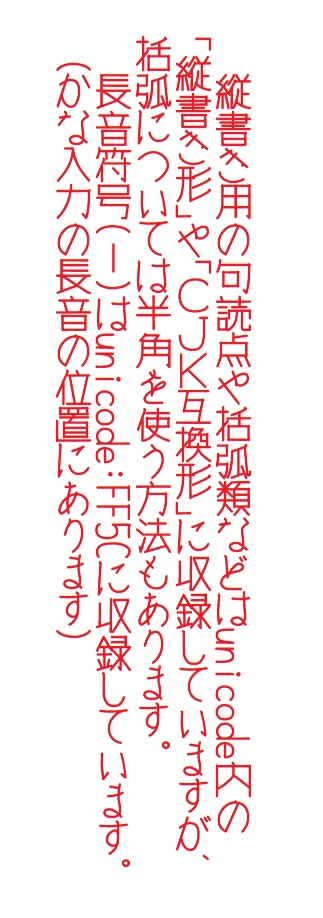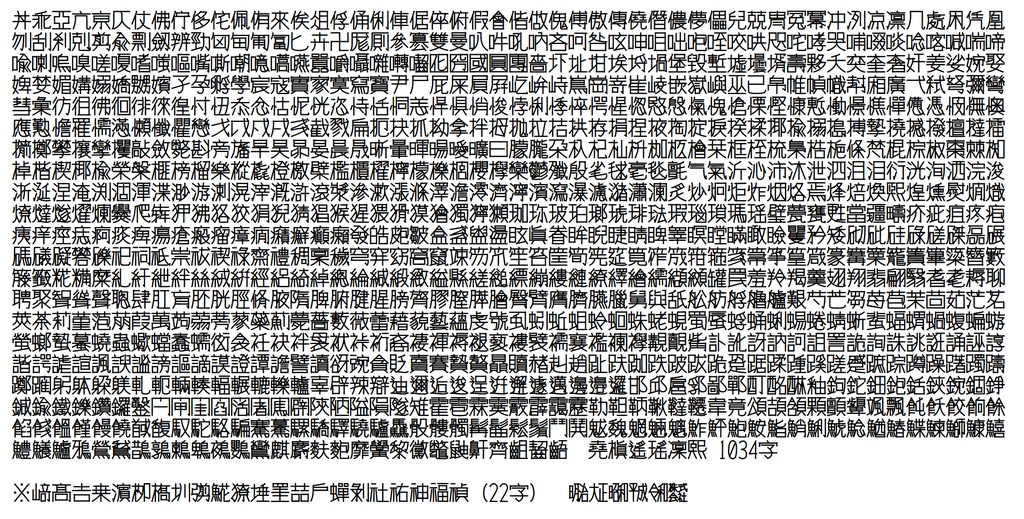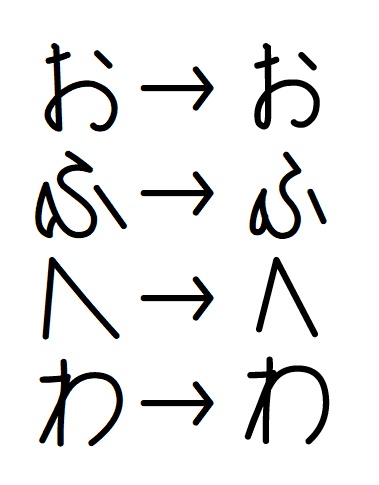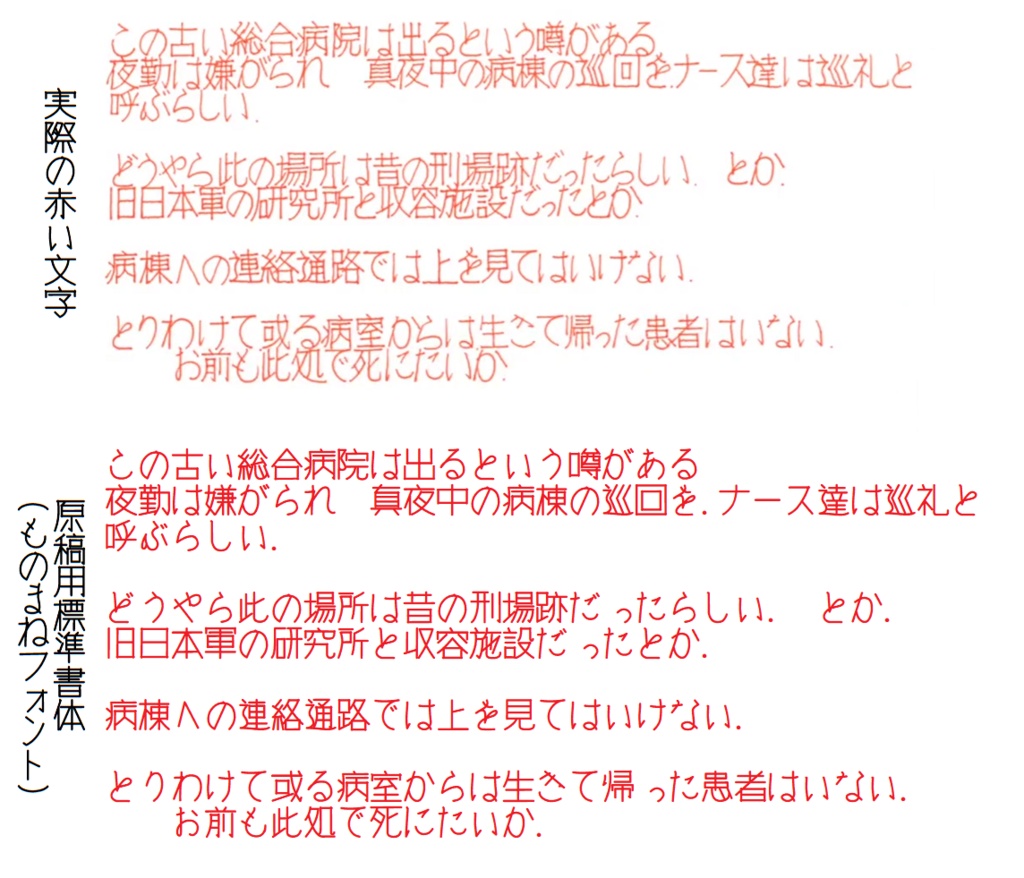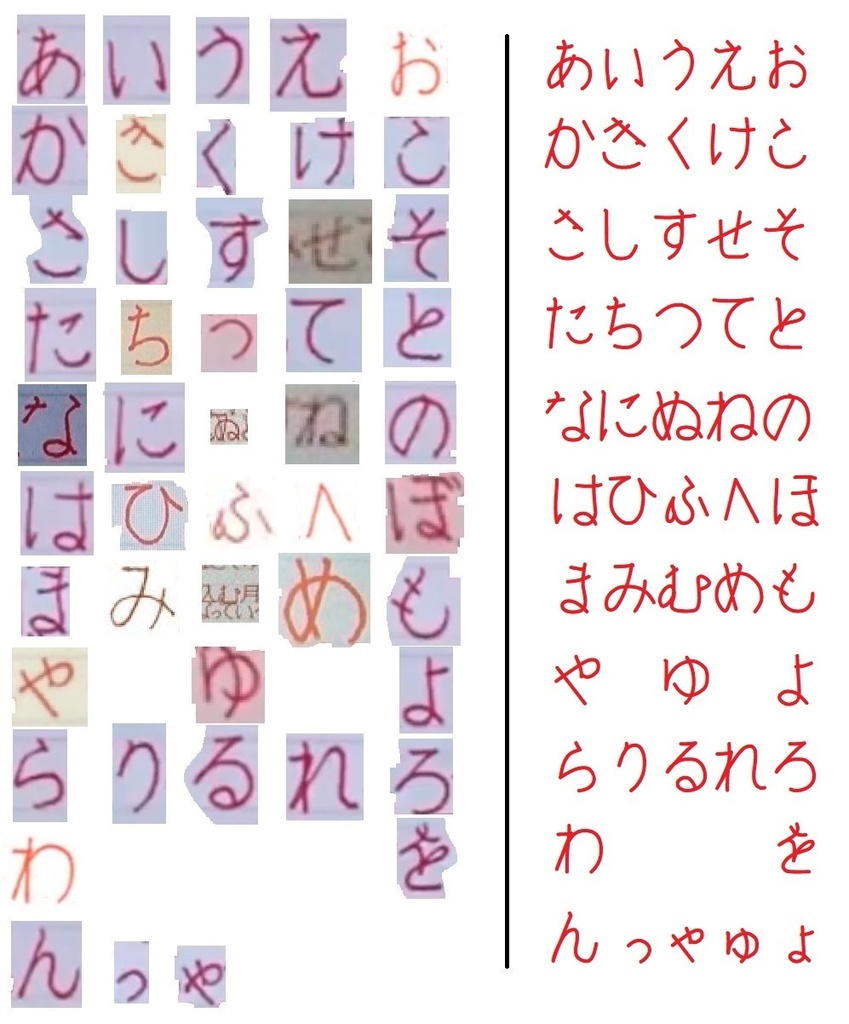
原稿用標準書体(2022/11/07再リニューアル)
このフォントは簡単に言うと稲●淳二風丸ゴシック体です。
詳しくは画像で。
同月28日:「せ」「ぜ」の字形を改善しました。
7月13日:【お詫び】「条」「墳」の2字がおかしいことになっていたため修正しました。
10月30日:実際に画像検索で探した赤い文字のひらがなとの比較画像を掲載。
2022年11月:「お」「ふ」「ぶ」「へ」「わ」の字形を
新資料から採取できた字形に合わせて変更。
(「ぷ」「べ」「ぺ」も変更、但し「ぉ」「ゎ」は据え置いた)